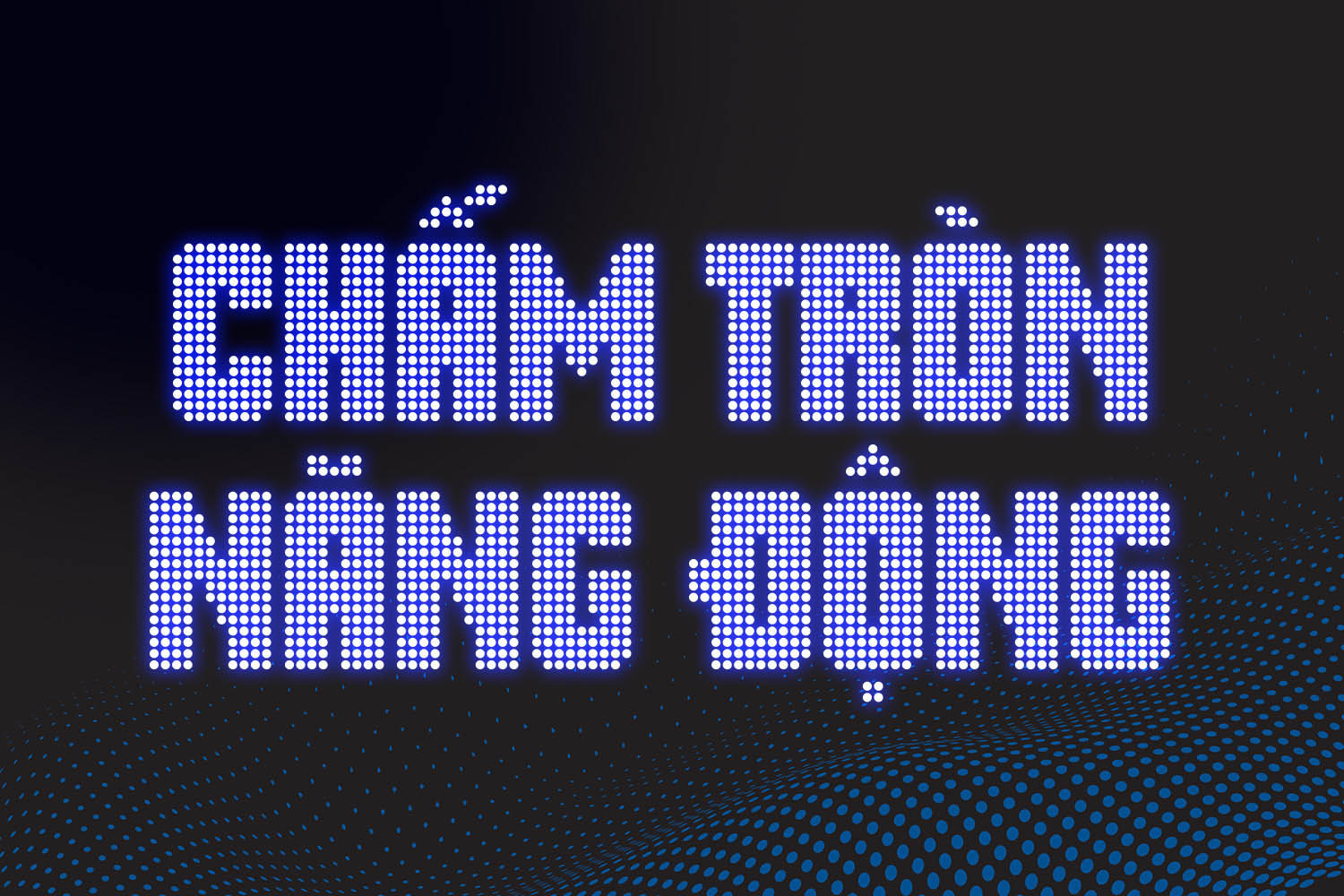
Font chữ chấm bi là gì và sức hút trong đồ họa hiện đại?
Font chữ chấm bi (Dotted Font) là phong cách phông chữ mà cấu trúc các ký tự được hình thành từ tập hợp những điểm tròn nhỏ sắp xếp theo một quy luật nhất định. Đặc trưng của bộ chữ này là mang lại cảm giác vui tươi, ngẫu hứng và đầy tính nghệ thuật đương đại. Thay vì các đường nét liền mạch thô cứng, kiểu chữ chấm bi tạo ra hiệu ứng thị giác thoáng đạt, gợi nhắc đến phong cách Pop Art hoặc xu hướng tối giản kỹ thuật số.
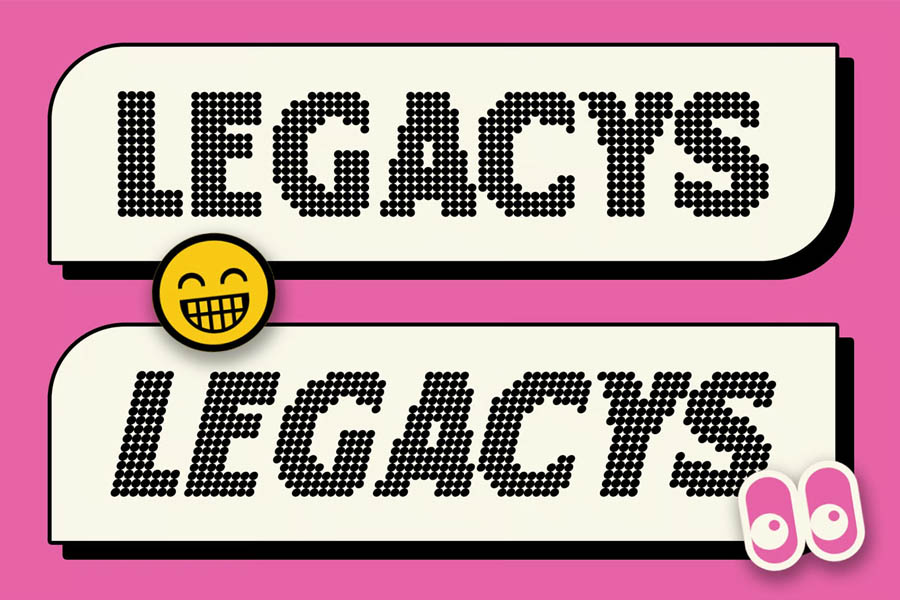
05 Ứng dụng phổ biến của font chữ chấm bi trong in ấn
Vẻ đẹp độc đáo và tính ứng dụng cao của mẫu chữ chấm bi giúp nâng tầm giá trị cho nhiều ấn phẩm truyền thông của đơn vị:
- Thiết kế bao bì bánh kẹo và thực phẩm thiếu nhi: Các mẫu chữ chấm bi mang lại sự hào hứng và vui vẻ, rất phù hợp để in trên các dòng vỏ hộp giấy Ivory hay túi giấy đựng bánh. Những chấm tròn rực rỡ tạo cảm giác ngon miệng và thu hút các bạn nhỏ ngay từ cái nhìn đầu tiên.
- Sản xuất bộ tem nhãn dán sticker: Phông chữ này cực kỳ lý tưởng để làm các mẫu sticker trang trí đồ dùng học tập hoặc nhãn dán niêm phong bao bì mỹ phẩm handmade. Độ sắc sảo của file giúp hình in rõ nét, tạo điểm nhấn cá tính cho sản phẩm thương mại.
- Gia công in UV trên các sản phẩm văn phòng: Logo và slogan dùng font chữ chấm bi được in trên bình giữ nhiệt kim loại hoặc sổ tay da tạo vẻ ngoài thời thượng. Công nghệ in tại In Viva giúp các hạt chấm nhỏ hiển thị sắc sảo, bền bỉ theo thời gian sử dụng.
- Trang trí thiệp mời sự kiện và voucher tri ân: Sử dụng kiểu chữ này cho các dòng thông điệp giúp ấn phẩm trở nên tinh tế và hiện đại. Sự kết hợp giữa nét chữ phá cách và kỹ thuật in ép kim nhũ vàng giúp tấm thiệp trở nên vô cùng bắt mắt.
- Đồng bộ bộ nhận diện biển bảng: Định dạng vector cho phép phóng lớn tiêu đề dùng phông chấm bi làm chữ nổi mica tại sảnh văn phòng hoặc trang trí showroom. Đường nét uyển chuyển của chữ giúp không gian làm việc toát lên sự đổi mới và trẻ trung.
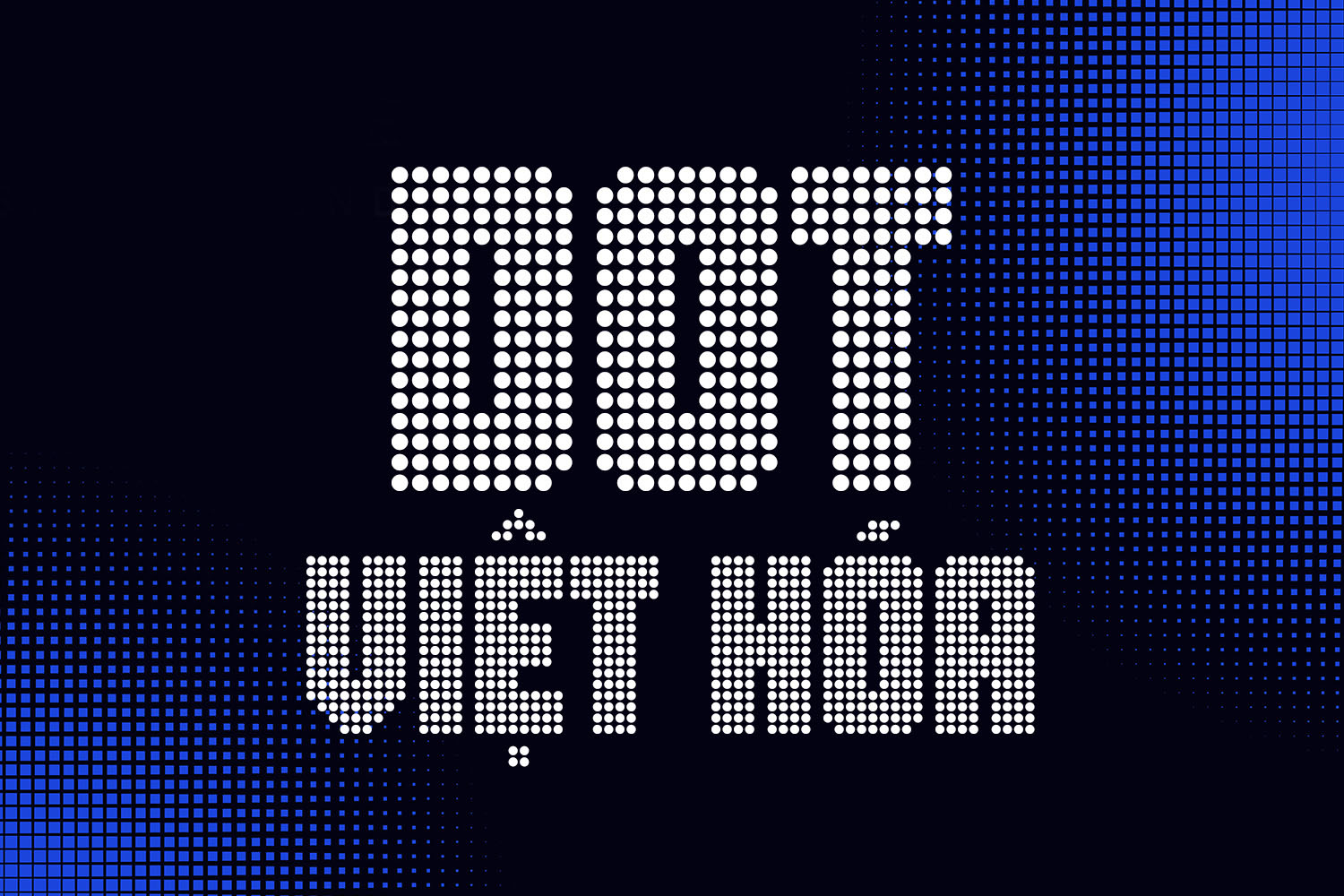
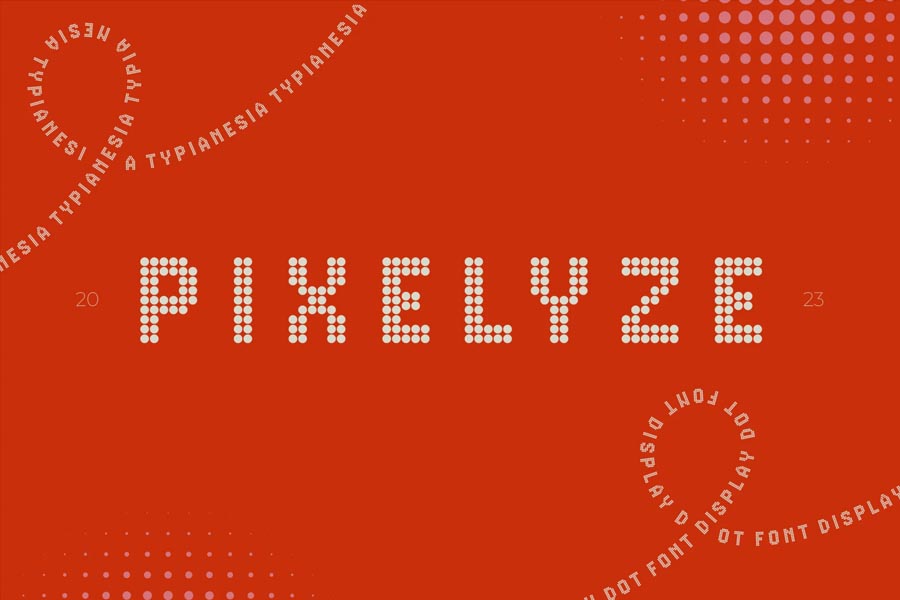
04 lưu ý kỹ thuật khi sử dụng font chữ chấm bi Việt hóa
Để hệ thống ký tự chấm bi hiển thị sống động và bền màu trên các thành phẩm thực tế như túi giấy cao cấp hay hiện vật tri ân đối tác, designer cần chú trọng:
- Kiểm soát mật độ điểm dot theo vật liệu: Khi in trên túi giấy Kraft có độ hút mực cao, bạn nên chọn mẫu font chữ chấm bi có khoảng cách giữa các chấm rộng hơn. Điều này tránh tình trạng mực bị loang làm các dấu chấm dính vào nhau gây mất dáng chữ.
- Tối ưu đường Path cho gia công bế nổi: Bước này quan trọng khi sản xuất nắp hộp cứng dập nổi logo doanh nghiệp. Kỹ thuật viên cần làm mượt từng điểm neo tròn trong file vector giúp khuôn bế thực hiện chính xác, tạo hiệu ứng nổi khối 3D rạng rỡ cho các dấu chấm mà không làm rách giấy mỹ thuật.
- Thiết lập hệ màu CMYK cho dải màu rực rỡ: Chữ chấm bi thường đi cùng các tông màu tươi sáng. Designer cần hiệu chỉnh hệ màu CMYK chuẩn và yêu cầu xưởng in mẫu thử để đảm bảo màu chữ sau in không bị ám xám hay mất sắc độ so với bản vẽ gốc.
- Điều chỉnh độ dày nét viền (Stroke): Khi thực hiện in lụa hoặc thêu trên vải túi canvas, bạn nên tăng nhẹ độ đậm của các dấu chấm trong file thiết kế. Việc này giúp mực in thoát đều qua lưới, đảm bảo hình ảnh hiển thị đầy đủ và không bị đứt đoạn nét chữ.